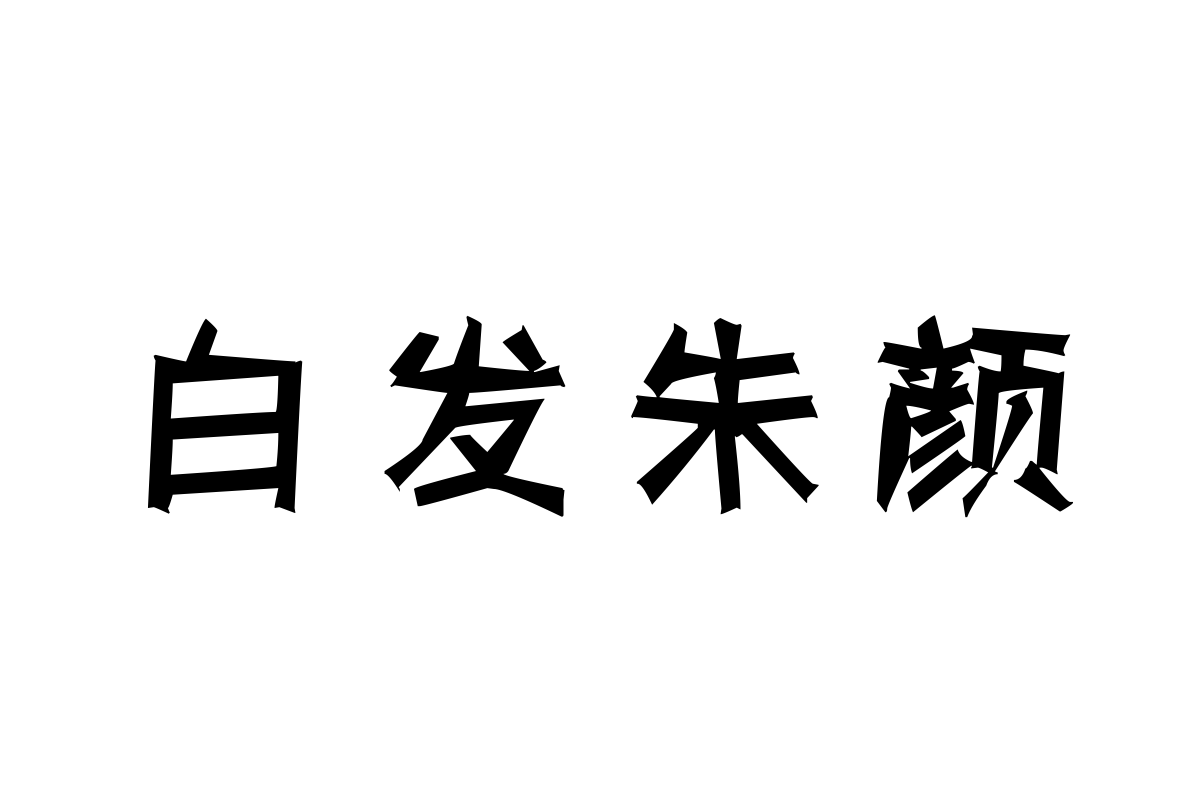
汉标扭扭体是一种手写字体,由汉标公司设计。这种字体具有独特的风格和特点,包括:
1. 笔画流畅:汉标扭扭体的笔画流畅自然,给人一种优雅的感觉。
2. 结构紧凑:每个字符的间距较小,使得整个字体看起来紧凑有序。
3. 易读性强:由于笔画流畅,所以这种字体的易读性非常好,适合用于阅读和打印。
4. 美观大方:汉标扭扭体的设计简洁大方,给人一种美感。
总的来说,汉标扭扭体是一种非常适合用于书写和打印的字体,它的设计和风格都非常适合需要强调个性和创意的场合。